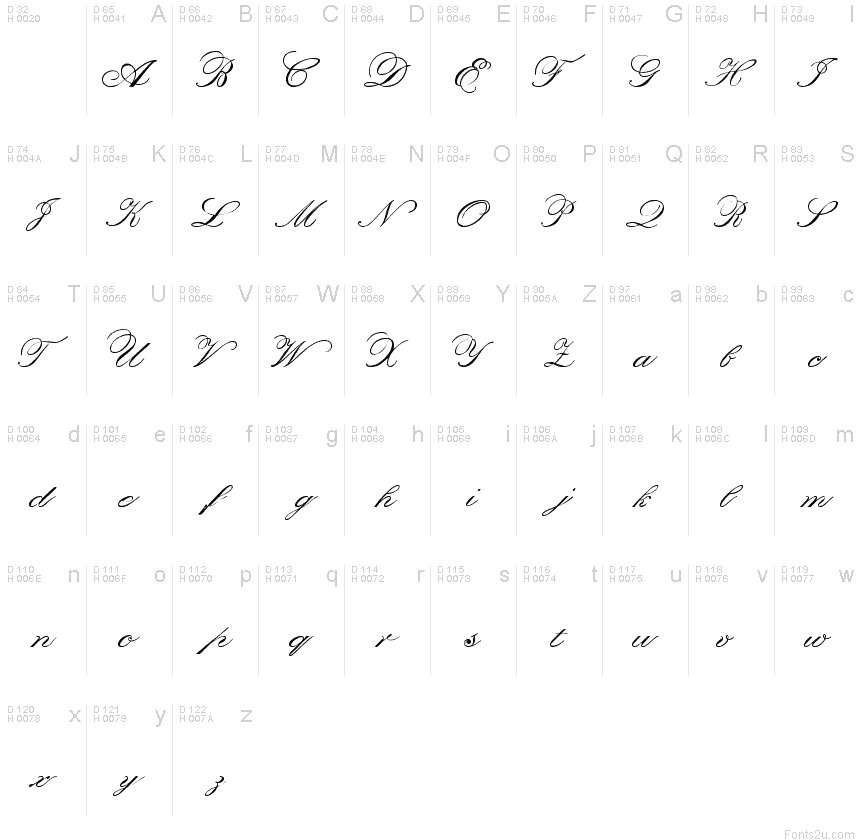
Orphiel autorstwa Davida Nalle to darmowy krój pisma kaligraficznego o długich, płynnych liniach i śmiałych, pętelkowych krzywiznach. Litery łączą się w jednym eleganckim ruchu, z wyrazistymi łączeniami i lekko formalnym, odręcznym rytmem, co nadaje mu pełnego wdzięku i lekkości charakteru.
Orphiel świetnie sprawdza się w zaproszeniach ślubnych, logotypach typu podpis, wizytówkach, opakowaniach butikowych czy ozdobnych cytatach, gdzie kaligraficzna linia może stanowić główny element strony. Ten darmowy font pasuje również do tytułów certyfikatów i papeterii osobistej, ponieważ jego płynne połączenia i wydłużone ozdobniki wprowadzają wyrafinowany, odręczny sznyt, nie sprawiając wrażenia przesadnie dekoracyjnego.